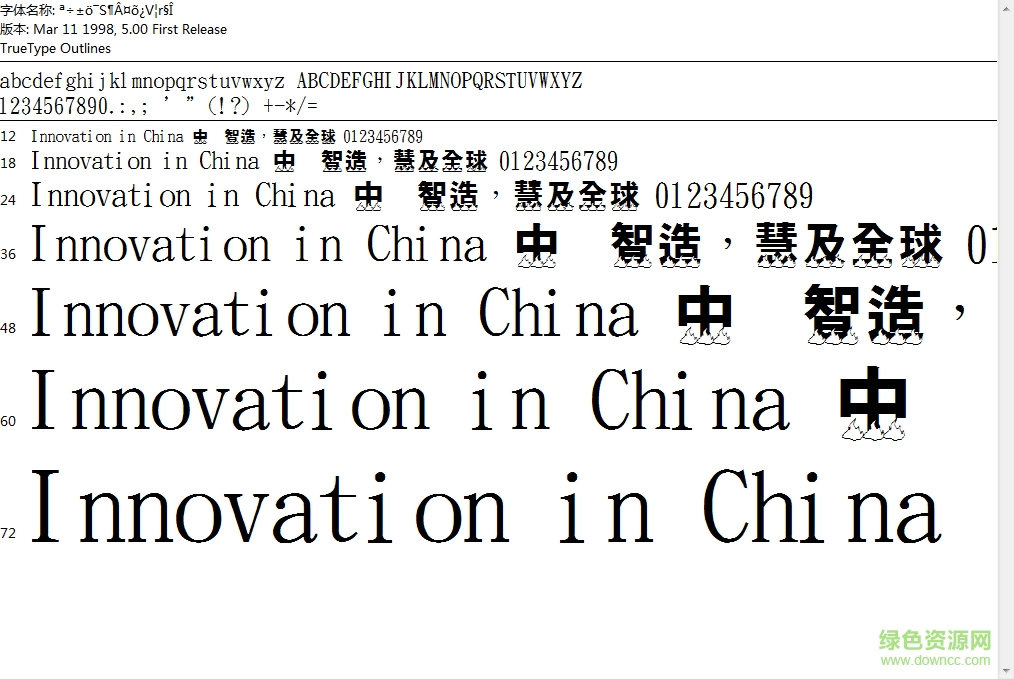
金梅特黑火焰字形是一款端正美觀的藝術(shù)字體,此款字體偏粗,每個字下面都有一團火,具有影人注目的特點,一般用在封面、標題、動漫比較多,喜歡的朋友歡迎來綠色資源網(wǎng)下載!
如果從設(shè)計的純角度來講,黑體運用的也是非常少的。黑體筆畫很均勻并且撇撩筆畫不尖,使人易于閱讀。由于其醒目的特點,常用于標題,導(dǎo)語,標志等等。當(dāng)然常見的標題、導(dǎo)語采用的是方正字庫里的粗黑,大黑,中黑,而不是我們WINDOWS里自帶的黑體。
與線比較相似,只是線比還要細,常用于時尚雜志的正文,與線筆畫橫平豎直、結(jié)構(gòu)醒目嚴密、便于閱讀,所以時尚雜志中比較常見,當(dāng)然,這一類字體不適宜在報廣(報紙廣告)的文字選擇,因為報廣印刷粗糙,細黑幾乎無法識別,但是在印刷精美的一些時尚雜志中,細黑與細等線會表現(xiàn)的非常精美。